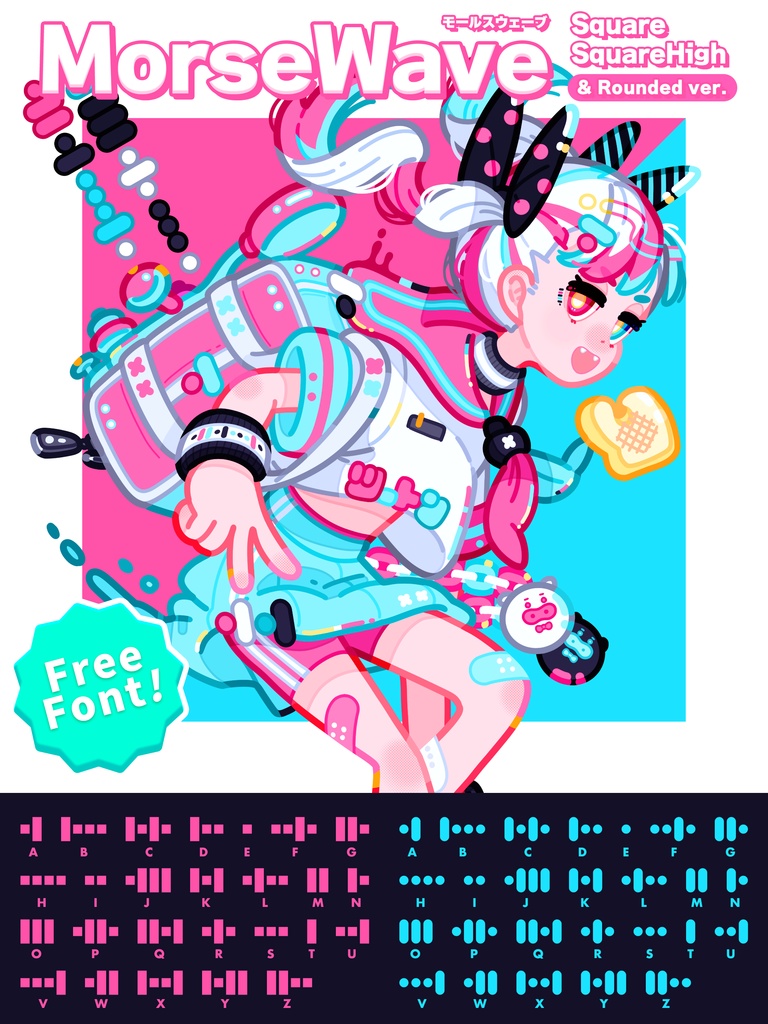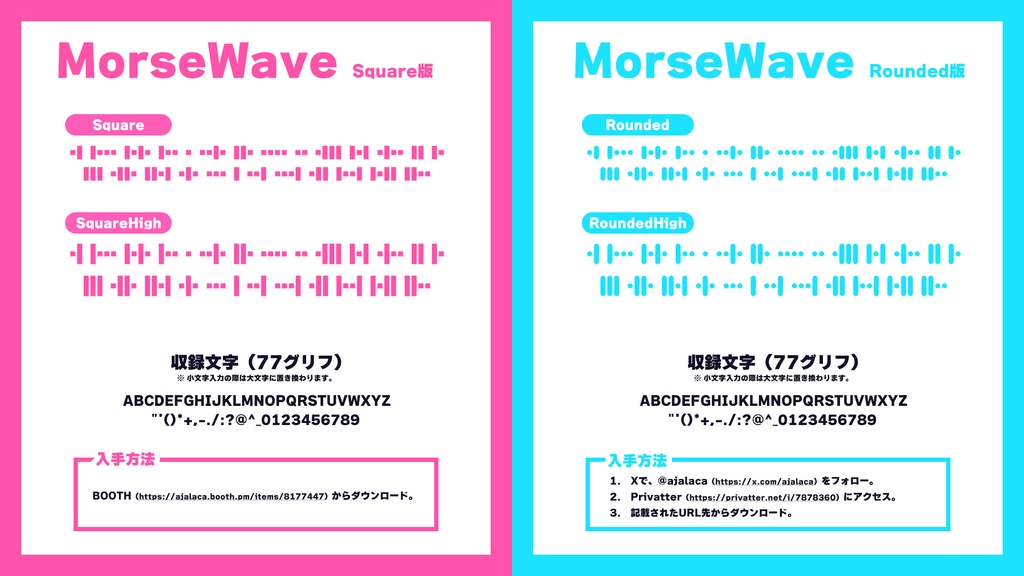
【フリーフォント】MorseWave(Square版)
【MorseWave(モールスウェーブ)】
モールス符号をモチーフにした、創作用欧文フリーフォント 📡
「・ー(トンツー)」の形状を高さに置き換え、アルファベット1文字と対応するようにデザインしました。あらゆる創作の素材や、秘密のメッセージとしてぜひご活用ください! ※ BOOTHでは、四角形状を収録した「Square版」を公開しています。